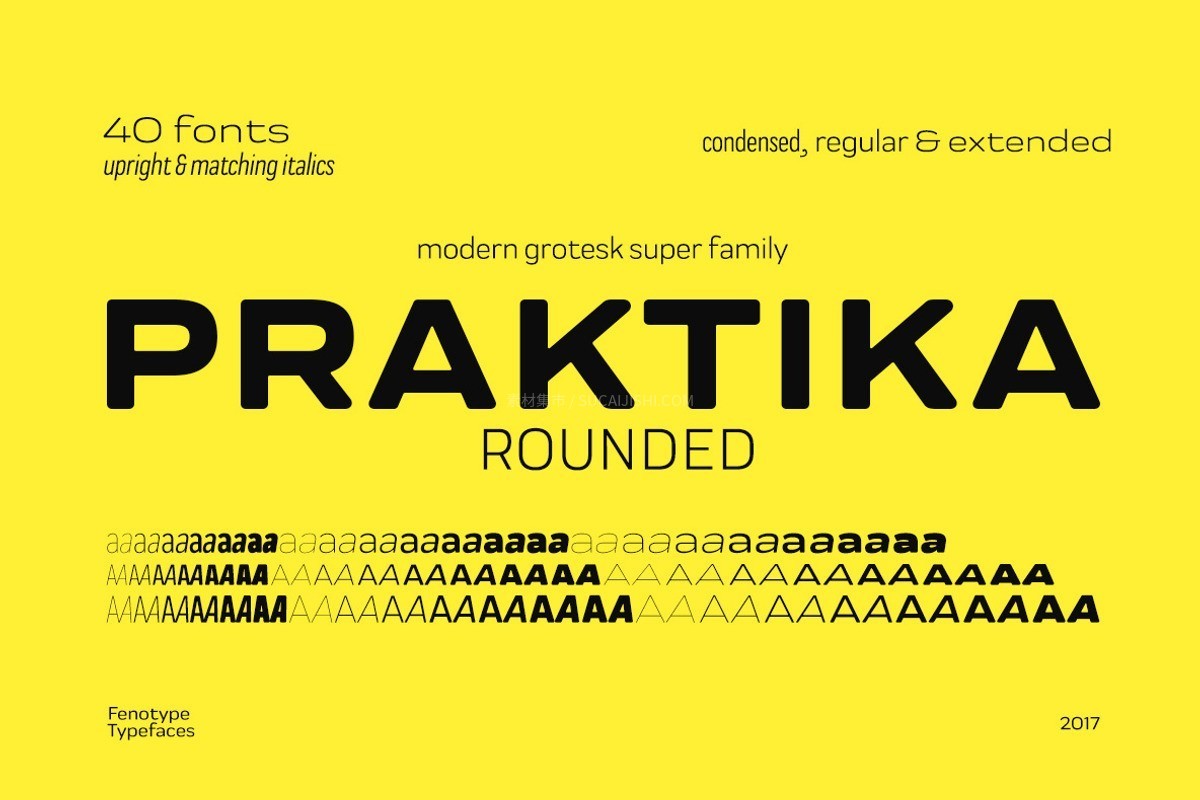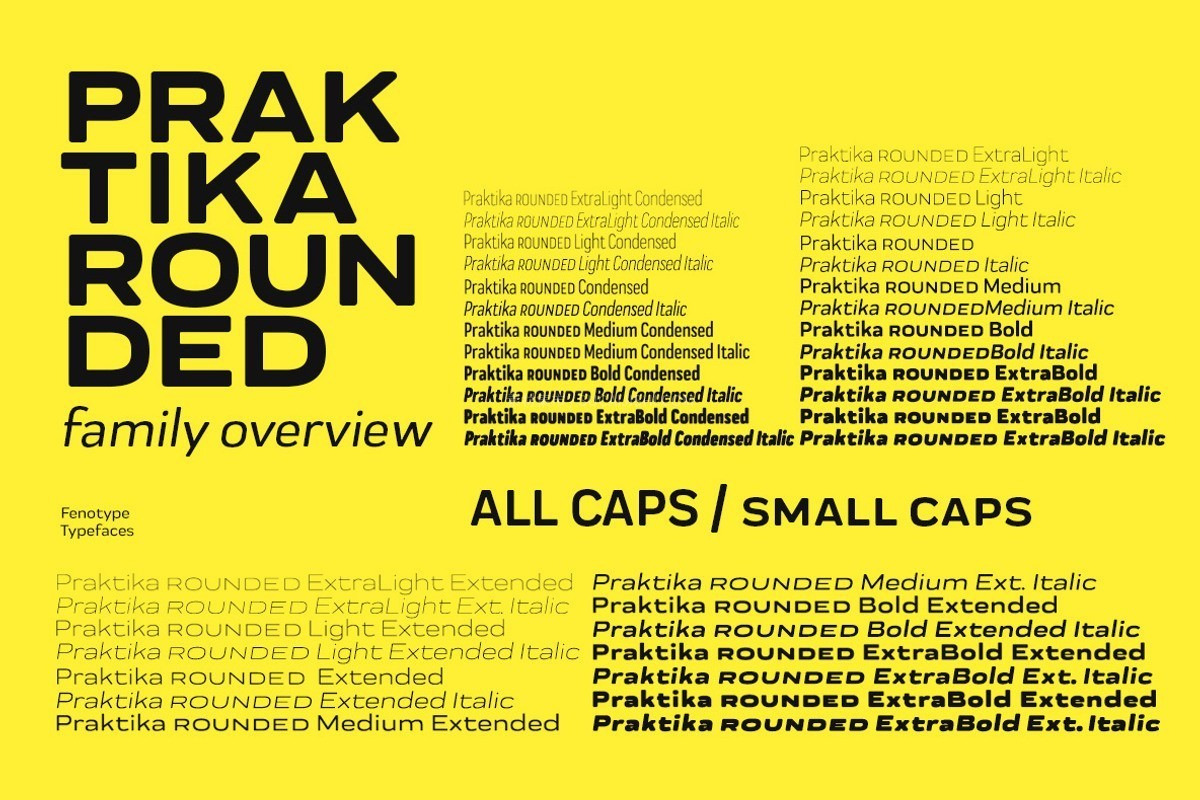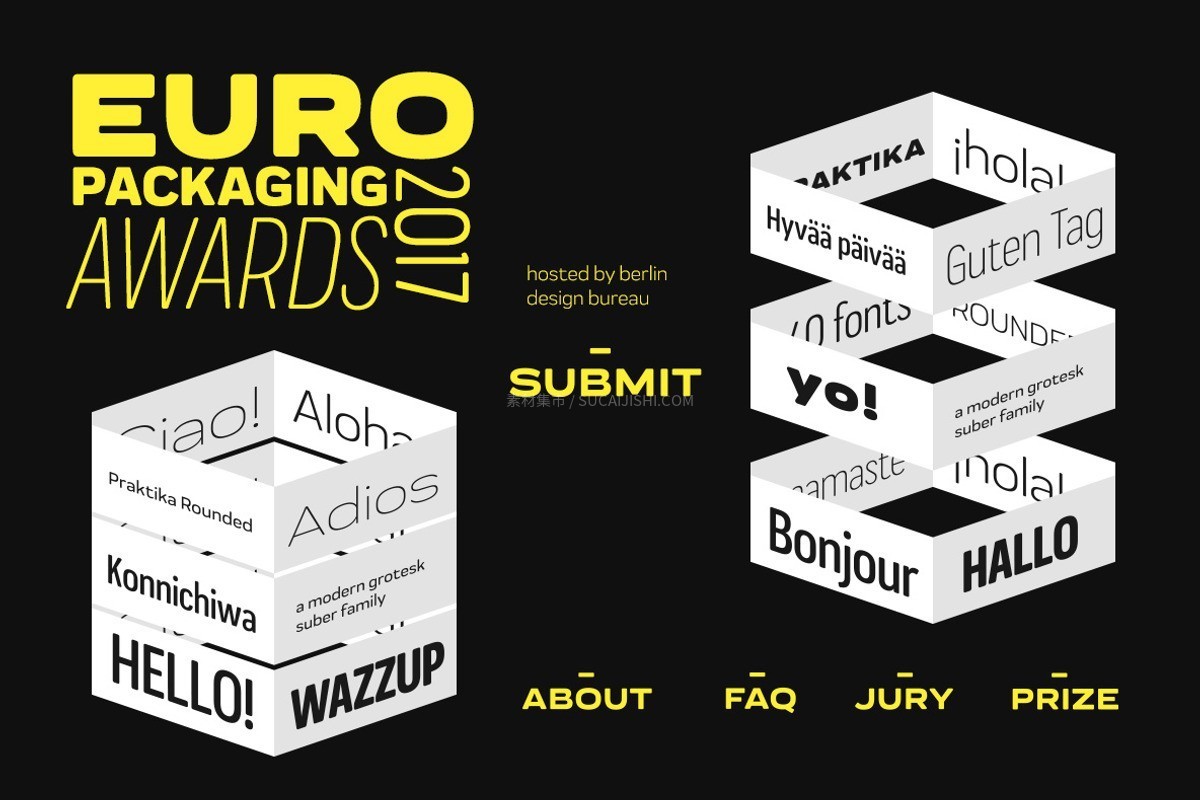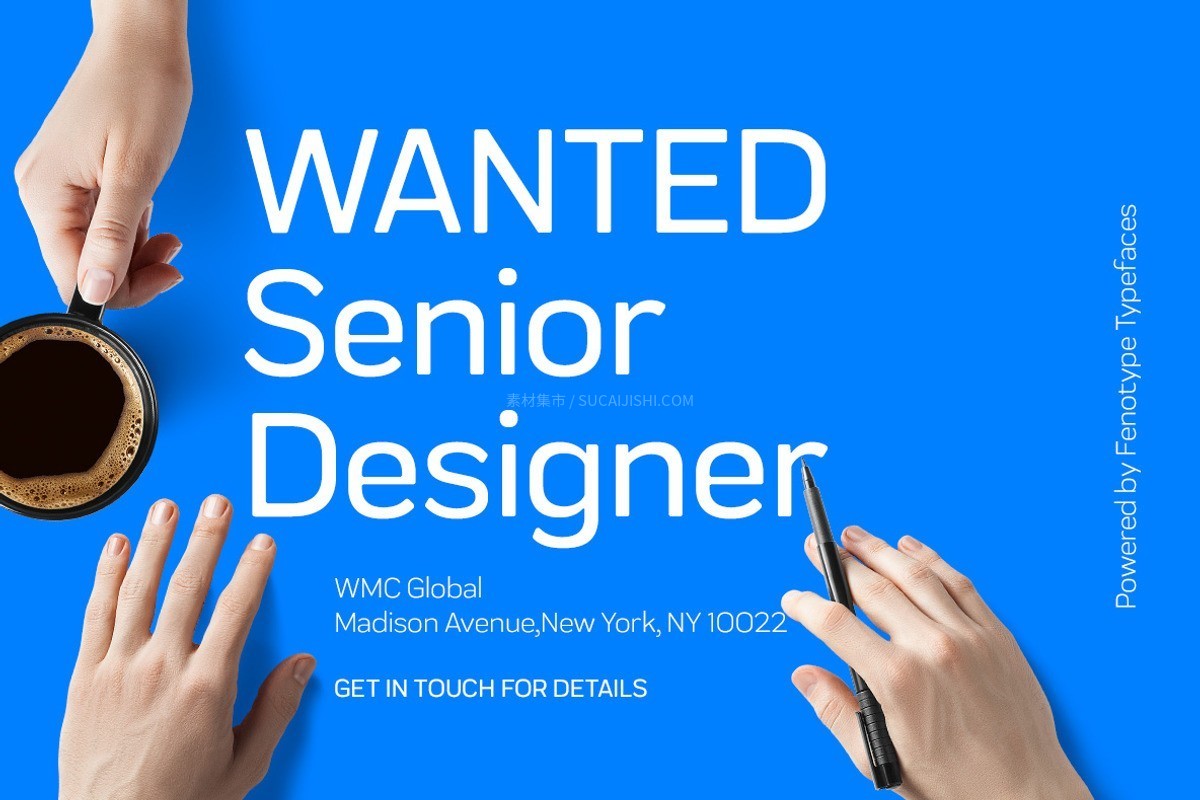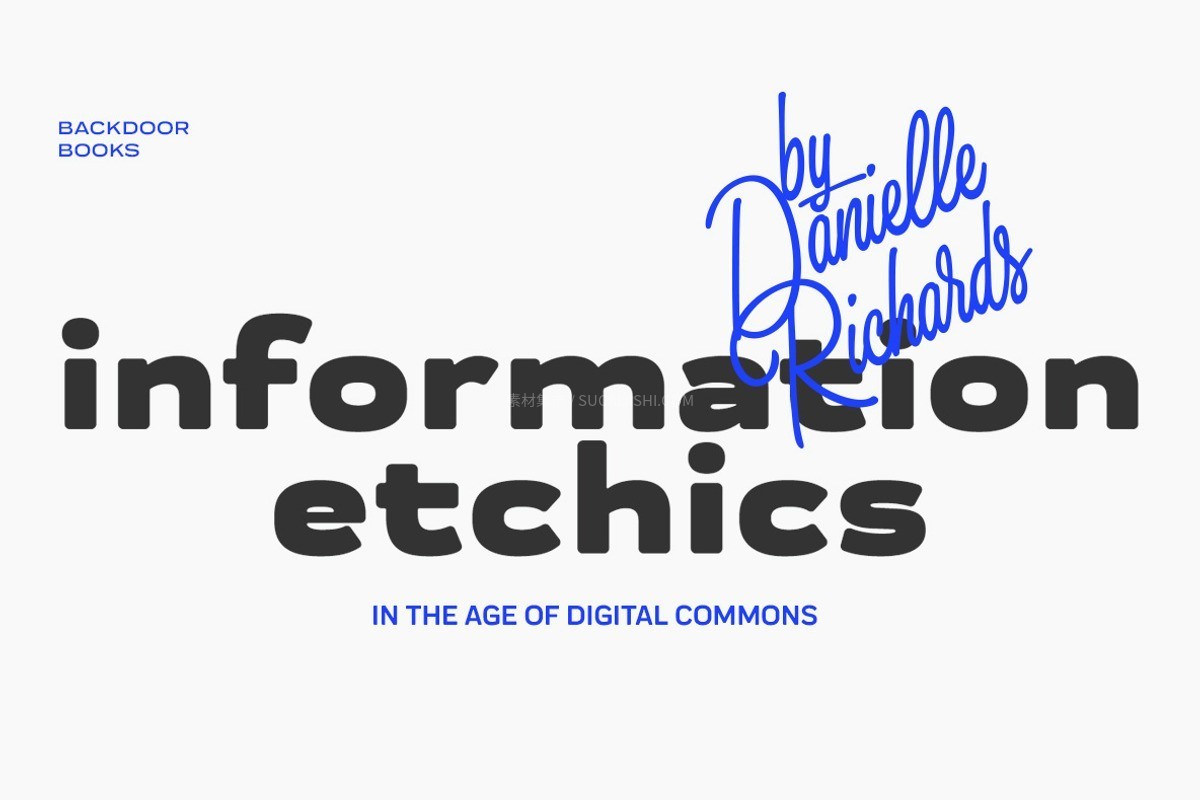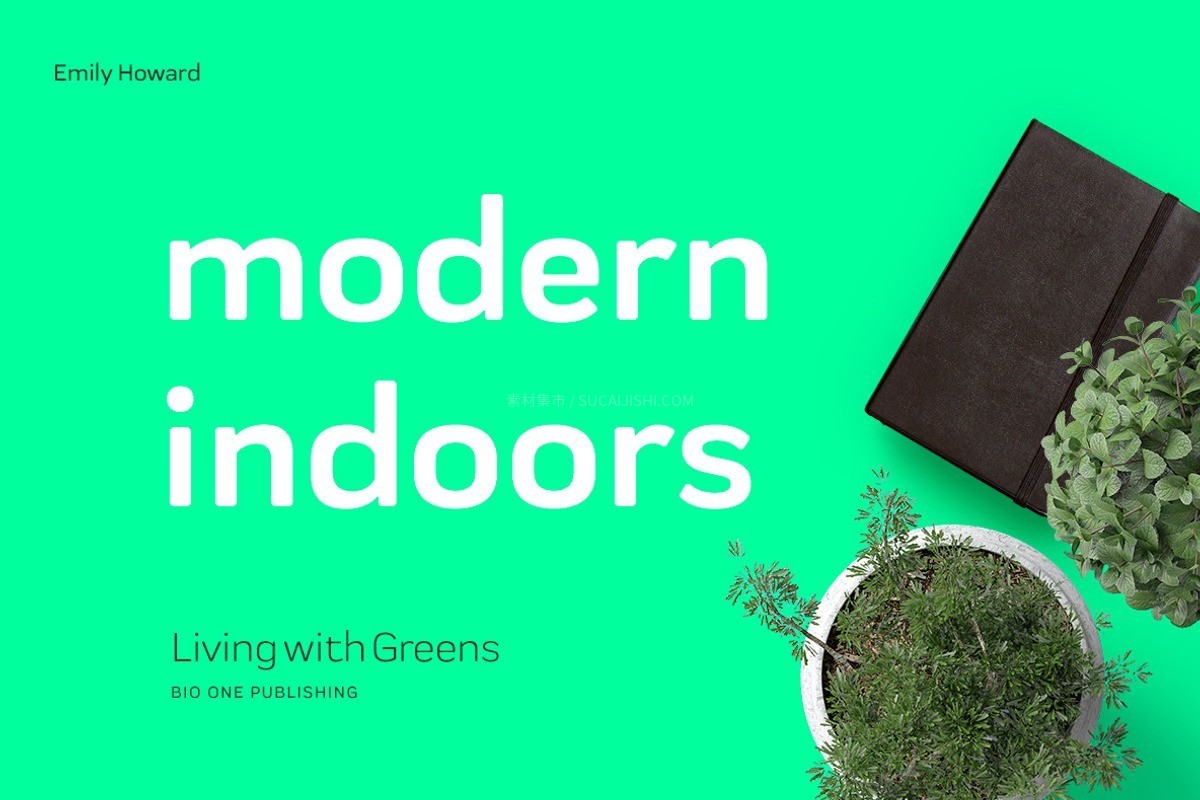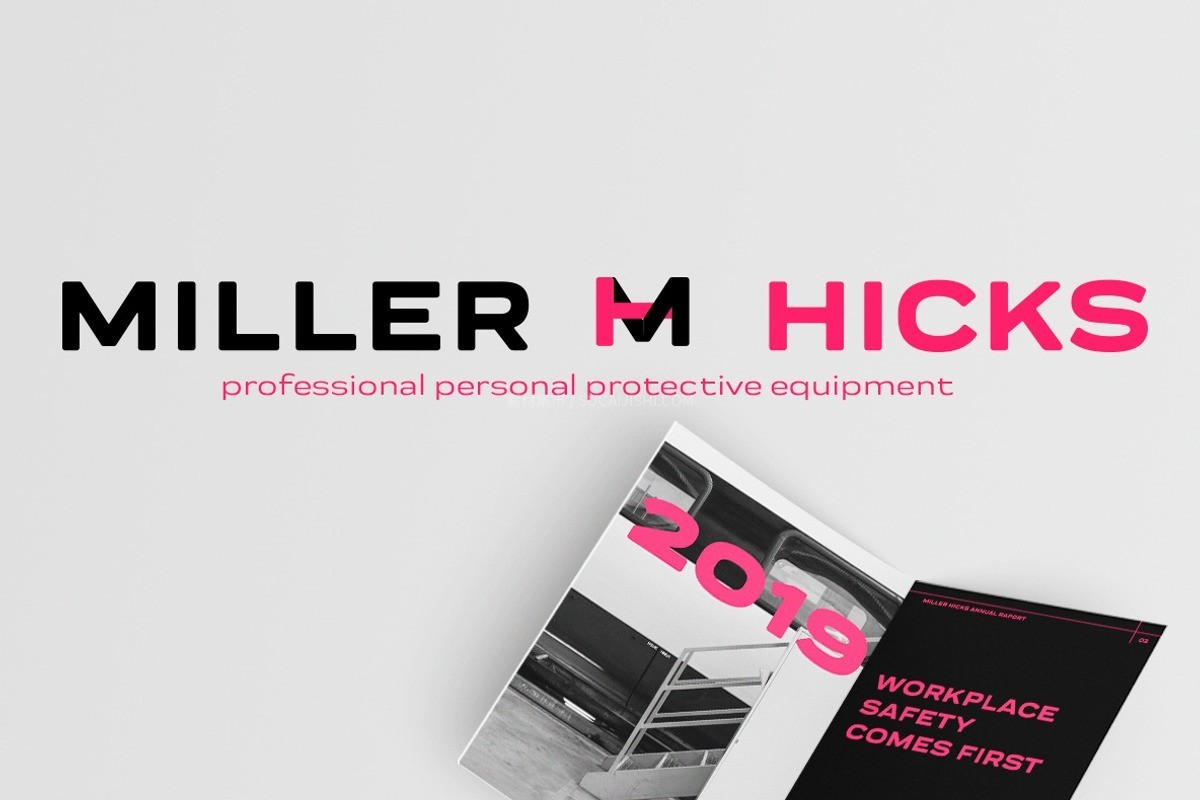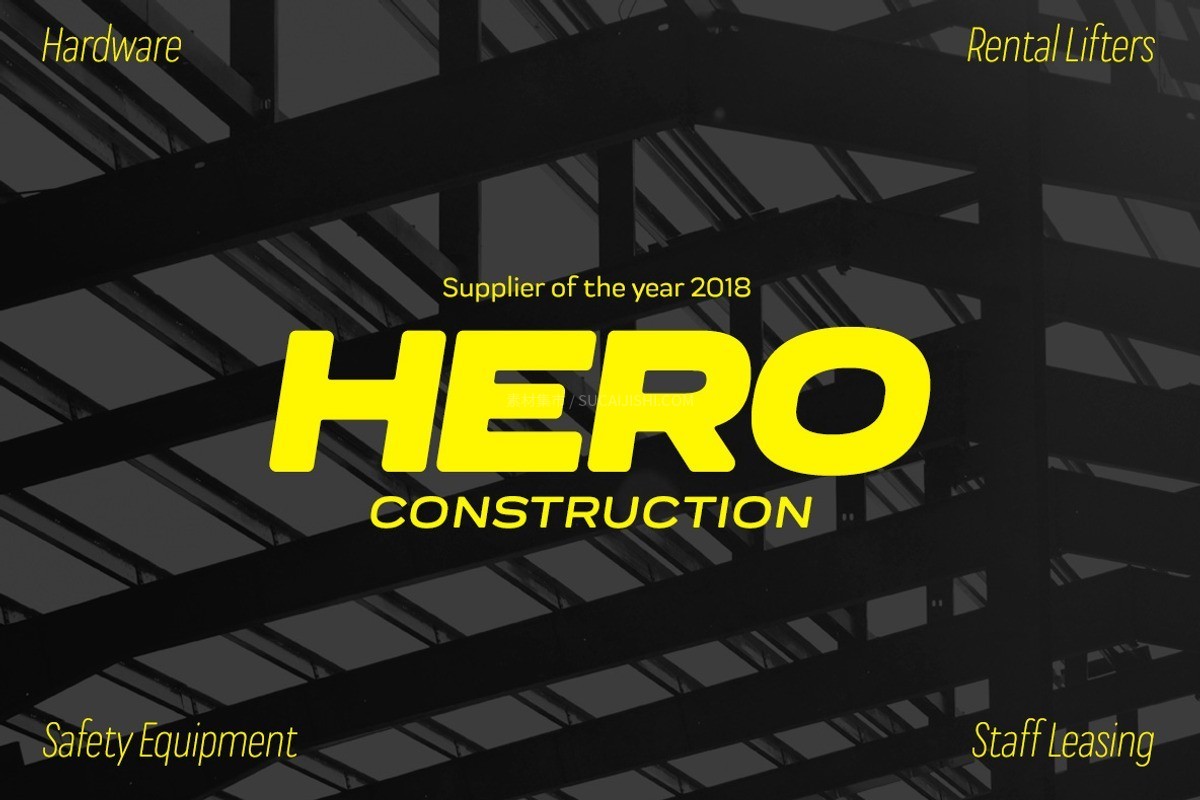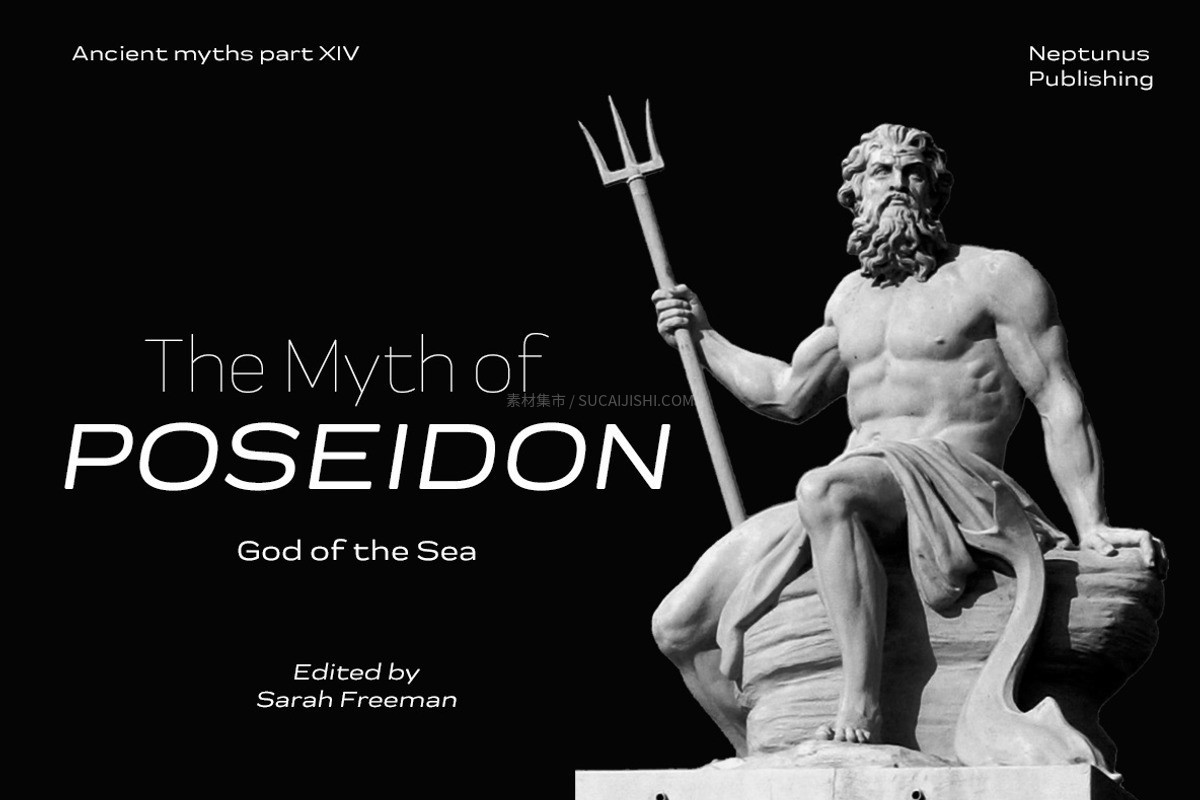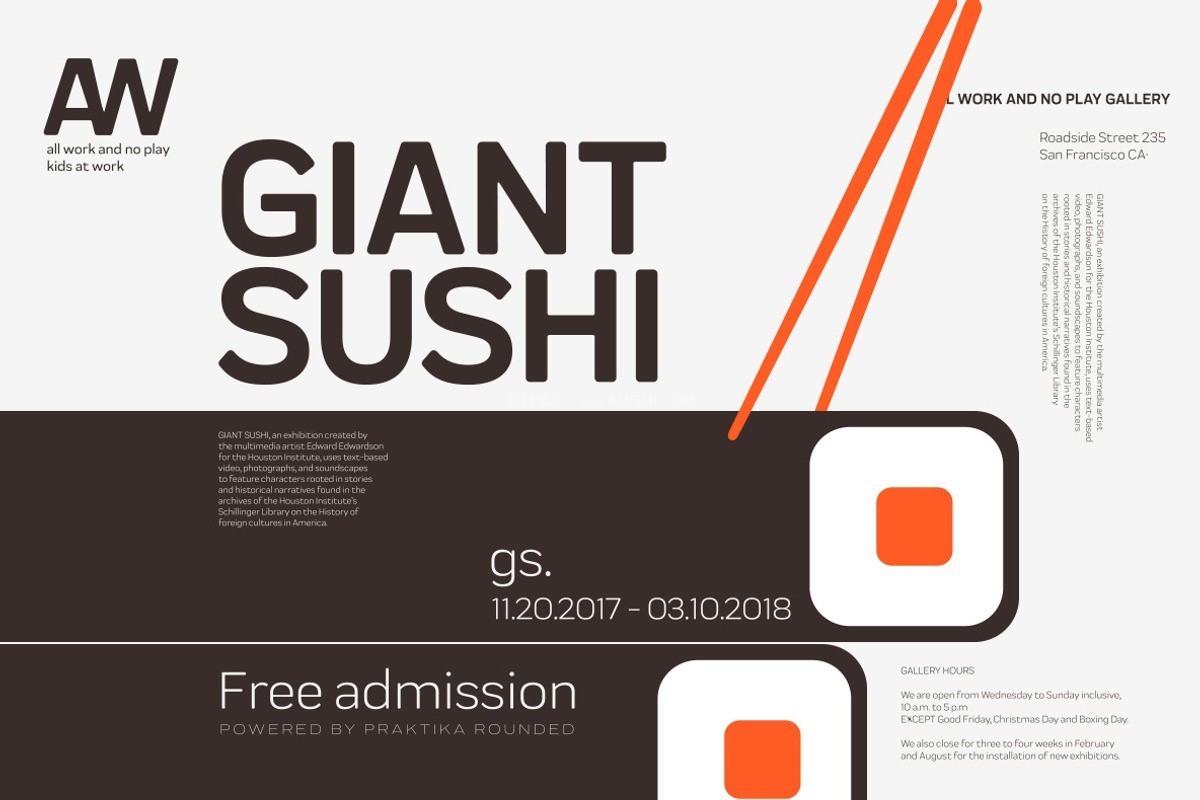
Praktika Rounded 现代都市风圆角字体完整版
Praktika Rounded 是 Praktika 系列的圆角版本,在继承前代产品强大功能的同时,注入了更具现代都市感的视觉灵魂。相较于古典风格,它更倾向于简洁、前卫的工业美学。该家族拥有极其庞大的系统:涵盖 7 种字重与 3 种字宽,能够应对极其复杂的排版挑战。
其内置的 OpenType 功能提供了专业级的排版支持:包括内置小型大写字母、多种样式的数字(等宽、旧式、表格或比例形式)、上下标数字以及丰富的替换字符,确保在每一个设计细节上都无可挑剔。